「近未来・SF」におすすめの日本語フリーフォント
今回は「近未来・SF」のテーマにぴったりなおすすめ日本語フリーフォントをまとめてみました。
現代的ではなく、ちょっと近未来でかっこいいフォントを中心にご紹介します。
近未来・SFをテーマとしたデザインを制作される際、未来をテーマにしたセミナーバナー、SFの同人誌・アニメ・マンガのタイトルロゴを制作する、近未来の映像制作をする際など、さまざまなシーンで活躍できるフォントです。
近未来・SFにぴったりな日本語フリーフォントまとめ
以下のサンプル画像は本記事で紹介している一部ですが、「近未来・SF」の雰囲気にぴったりな日本語フリーフォントをピックアップしてみました。
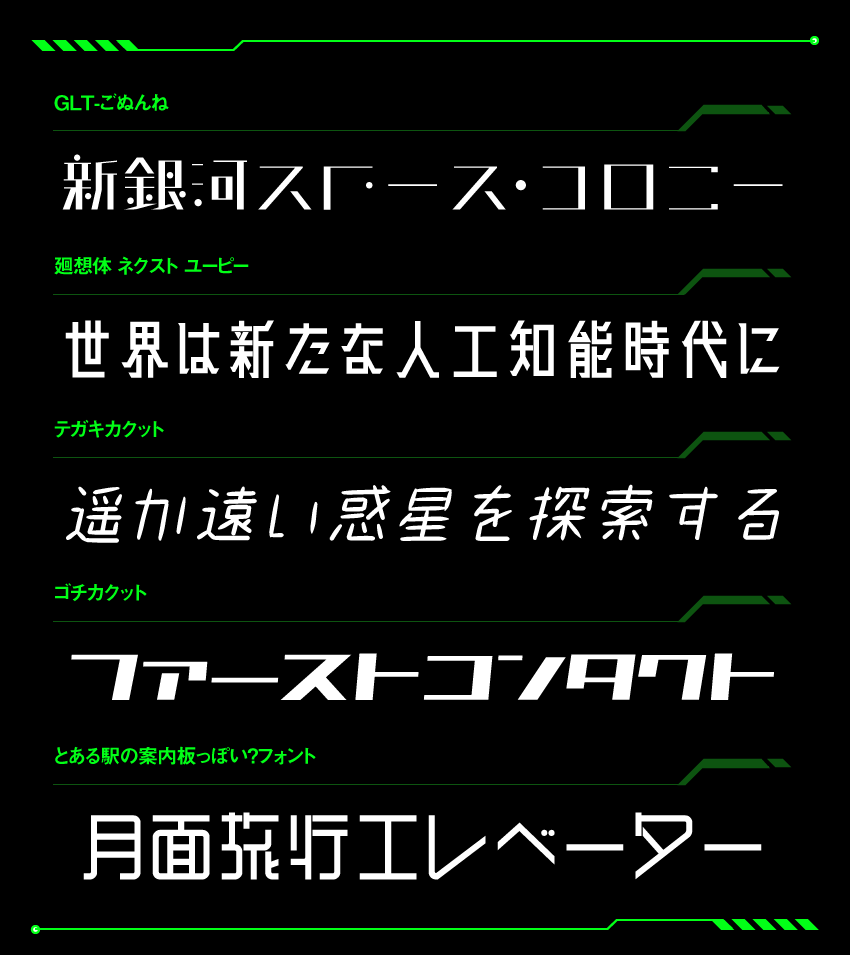
GLT-ごぬんね
GLT-ごぬんねフォントは、未来を題材としたアニメのロゴからヒントを得て制作されたフォントです。
文字に癖があり、文字の一部がドットのような丸の形状になっているので、ユニークです。
廻想体 ネクスト ユーピー
廻想体 ネクスト ユーピーフォントは、無機質な直線で構成されているフォントです。
直線的な線のみで作られているので、曲線がないところが、少し近未来感を感じさせてくれます。
マキナス
マキナスフォントもまっすぐな線の組み合わせで作らているフォントです。
人肌や温度感がないように見えるので、近未来やSFのようなロボットのような人間味を感じない無機質な表現ができる近未来フォントです。
せのびゴシック
せのびゴシックフォントは、「M+ FONTS」を機械的に70%のコンデンスド風(長体風)に加工されたフォントです。
長体に変形されていることで、スマートに見えるため近未来感を感じるフォントです。読みやすさもあるフォントなので、近未来の表現と可読性のバランスが良いフォントです。
テガキカクット
テガキカクットフォントは、手書きの雰囲気もありますが、デジタル時計の数字のようにも見えるフォントです。
未来感あるデジタル感とアナログ感を感じるユニークなフォントです。
瀞ノグリッチ明朝
瀞ノグリッチ明朝フォントは、映像が乱れたノイズのようなグリッチ表現が文字に加えられているフォントです。
ザザザっとノイズが入っている部分に、電脳感がありSFちっくな雰囲気を感じます。
加工が加えられているフォントですが、明朝体をベースとしているので、しっかりと読みやすく・わかりやすいフォントです。
ニコ角
ニコ角フォントは、ニコニコ動画のロゴをベースに制作されたフォントです。
カタカナがロボットアニメに使われていそうなSF感があって素敵なフォントです。
ゴチカクット
ゴチカクットフォントは、カクカクとした直線的なフォルムはロボットアニメのタイトルなどにも使われいそうなフォントです。
無機質な作りと、ほかフォントにはないクセが良い近未来的な印象を作り出しているフォントです。
鉄路タイプフェイス
鉄路タイプフェイスフォントは、切り込みが入っている、未来のメカやロボットに刻印されている文字のようなフォントです。
ガンダムやエヴァンゲリオンのようなロボットの機体に入っている文字ようなカッコよさがあるフォントです。
漢字の文字数が少なめのフォントなので、本文などよりタイトルなどに取り入れてみると良いかもしれません。
とある駅の案内板っぽい?フォント
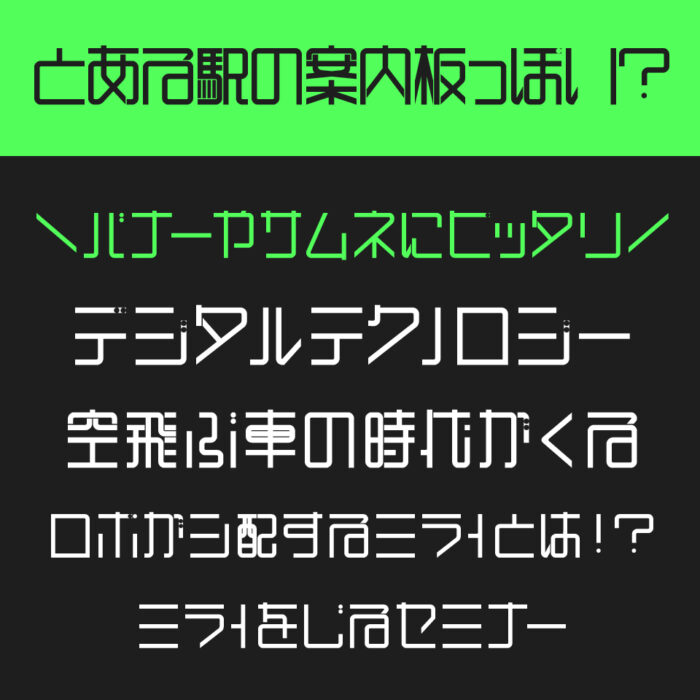
とある駅の案内板っぽい?フォントは、駅構内の案内表示をガムテープを使って書かれた文字「○悦体」をオマージュして作られたデザインフォントです。
直線的で、幾何学的なデザインがSF感を感じさせるのかもしれません。